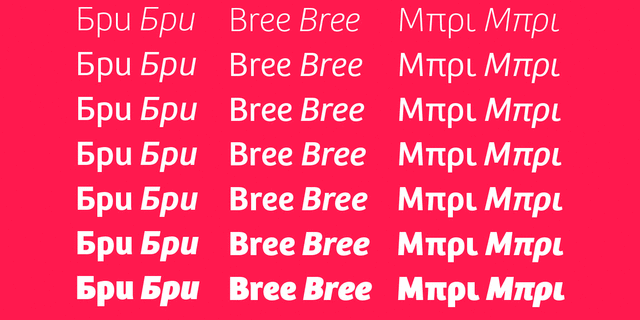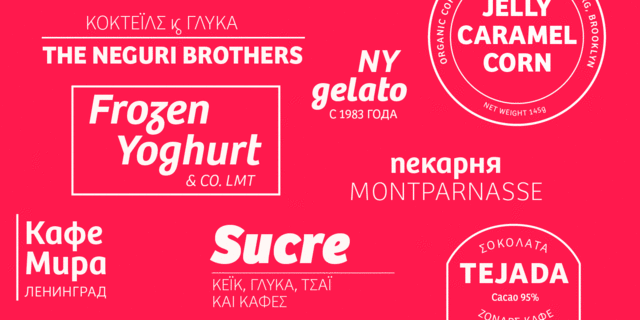
Bree – это динамичный гротеск, придающий особый характер любому тексту в брендинге и заголовках. Формы прямого курсива создают приятное сочетание ненавязчивых заглавных букв с более яркими строчными, что придает тексту живой вид. Шрифт создан под влиянием дерзкого почерка, проявляющего неординарную личность. В семейство входят 7 прямых начертаний, 7 курсивных и 2 вариативных начертания. Bree получил бронзовую награду на Европейском Фестивале Дизайна 2009. Гарнитуру разработали Вероника Буриан и Хосе Скаглионе в 2008-2019 году.